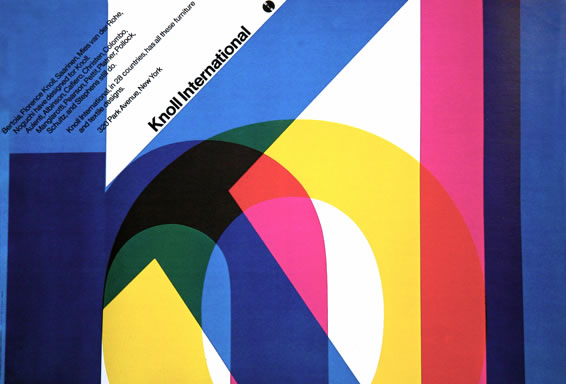
Estilo InternacionalO «International Style» designa a expansão da Escola Suíça por todo o mundo. Este movimento teve adeptos na Alemanha, nos EUA, na Àsia e em muitos outros países e regiões. Na sua renúncia à exteriorização de sentimentos pessoais e subjectivos, ou às técnicas propagandísticas de persuasão da publicidade comercial, Müller-Brockmann, mentor do Estilo Suíço, alinhou pela vereda da «despersonalização» do design uma orientação que convinha à expansão do Capitalismo na etapa imediata ao pós-guerra. O «universalismo» do Estilo Internacional fez repetir continuamente os mesmos padrões. A monotonia começou a reinar no Desenho gráfico, na Arquitectura, na sinalética, no desenho editorial, na tipografia, etc. Em breve, quase todas as agências de comunicação forneciam um trabalho indistinto e entediante. A fonte Helvetica era a campeã do Estilo Internacional...